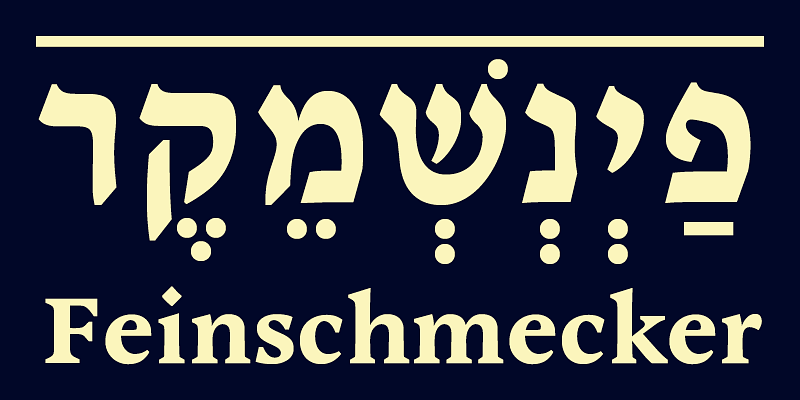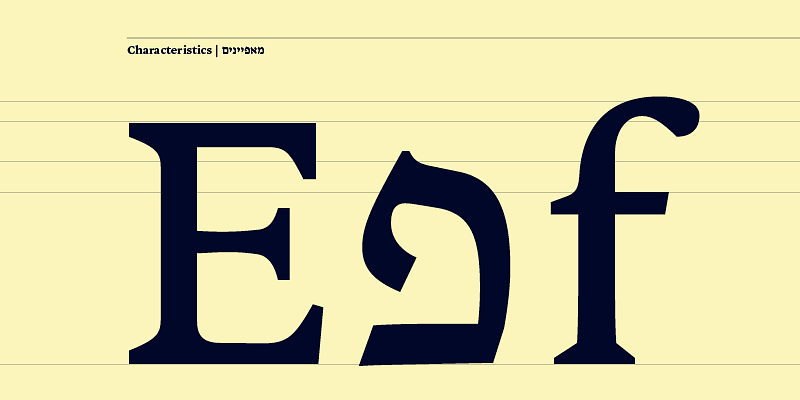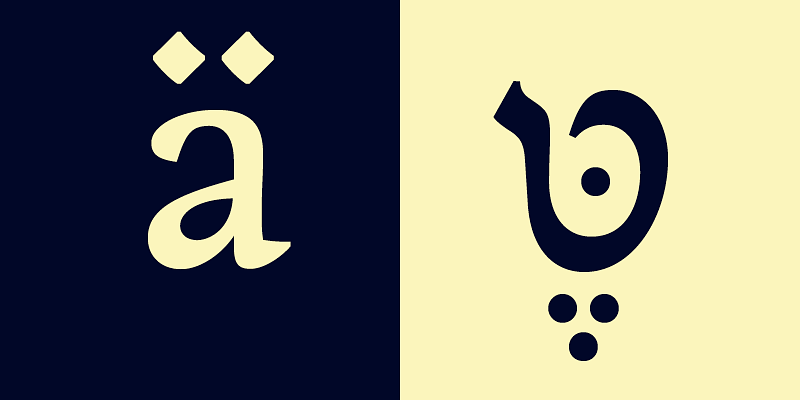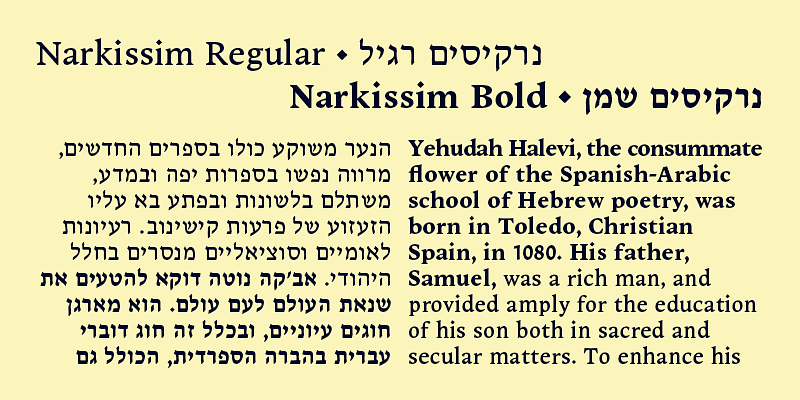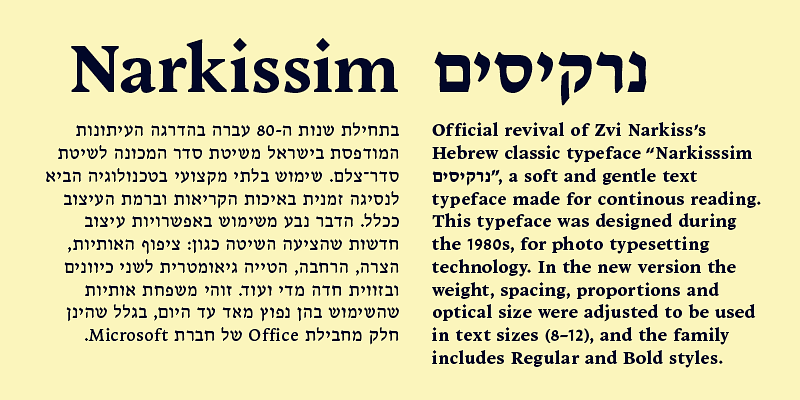
Revival officiel de la police de caractères classique hébraïque de Zvi Narkiss « Narkissim נרקיסים », une police de texte douce conçue pour une lecture fluide. Cette police de caractères a été conçue dans les années 80, pour la technologie de photocomposition. Dans la nouvelle version, l’épaisseur, l’espacement, les proportions et la taille optique ont été ajustés pour être utilisés dans les tailles de texte (8 à 12), et la famille comprend les styles Regular et Bold.
Depuis 2019, Fontef est le distributeur exclusif des polices de caractères hébraïques classiques conçues par Zvi Narkiss [1921-2010]. Nous avons créé de nouvelles versions numériques de toutes ses polices de caractères, avec le latin correspondant, et un site Web spécial où vous pouvez jouer avec elles ici.